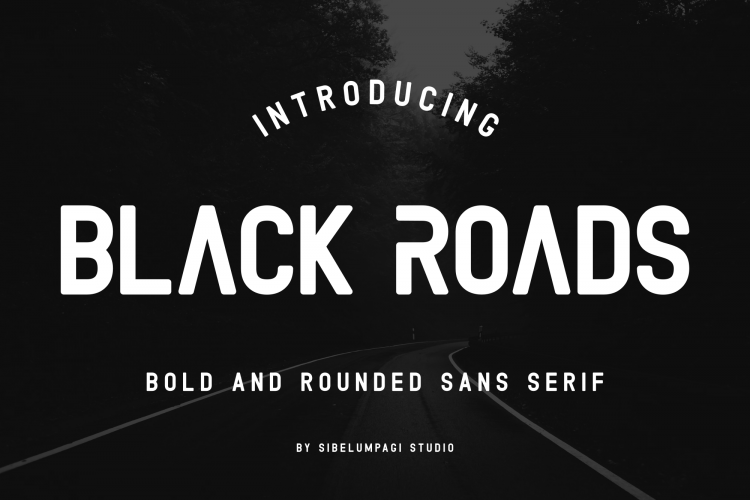
Black Roads Typeface – Download Grátis
Olá pessoal! Estou aqui uma nova fonte de sans-serif bold e redonda chamada Black Roads Typeface. Introduzimos a BlackRoads Font. Esta fonte de sans-serif limpa e forte tem um formato bold e redondo, e vem com dois estilos: regular e outline. É uma escolha ótima para muitos projetos variados como logomarcas e branding, convites, etiquetas de estação, posts nas redes sociais, roupas, anúncios, embalagens de produtos, designs dos produtos, etiquetas, fotografia, marcadores d’água e eventos especiais ou qualquer coisa. Com certeza a Black Roads Typeface é uma fonte que vai se encaixar perfeitamente em diferentes ambientes de design. Descubra mais sobre nossa série ‘Black Roads Typeface’, disponível no download aqui.